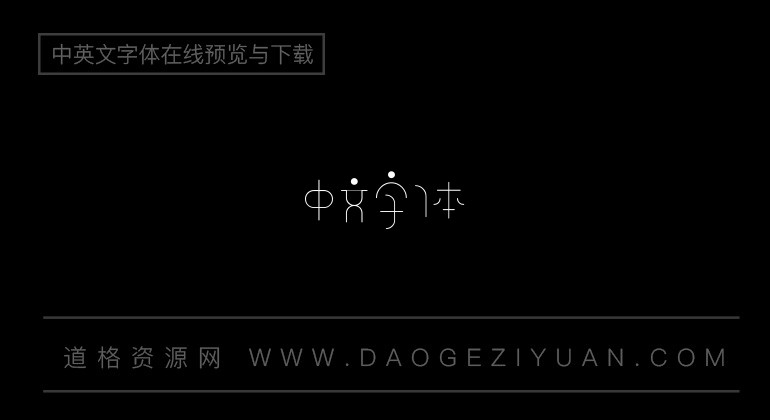
锐字工房卡布奇诺美瞳简字体是一款由锐字工房设计的汉字字体,采用简洁明快的设计风格,让字体拥有精致的外形。它采用了比较细腻的线条,让字体看起来更加精致,更有深度。字体的字形设计更加精细,更具有立体感,能够更好地表达出文字的精神内涵。此外,该字体还具有良好的可读性,能够更好地传达文字的意义,让读者更容易理解文字的内容。文件名:RuiZiGongFangKaBuQiNuoMeiTongJian-1.otf
锐字工房卡布奇诺美瞳简是一款非常不错的手写艺术字体,具有很好的视觉感,适合于文化类的宣传设计、商业类品牌的广告和产品包装设计以及个性化文字排版等较多场景。